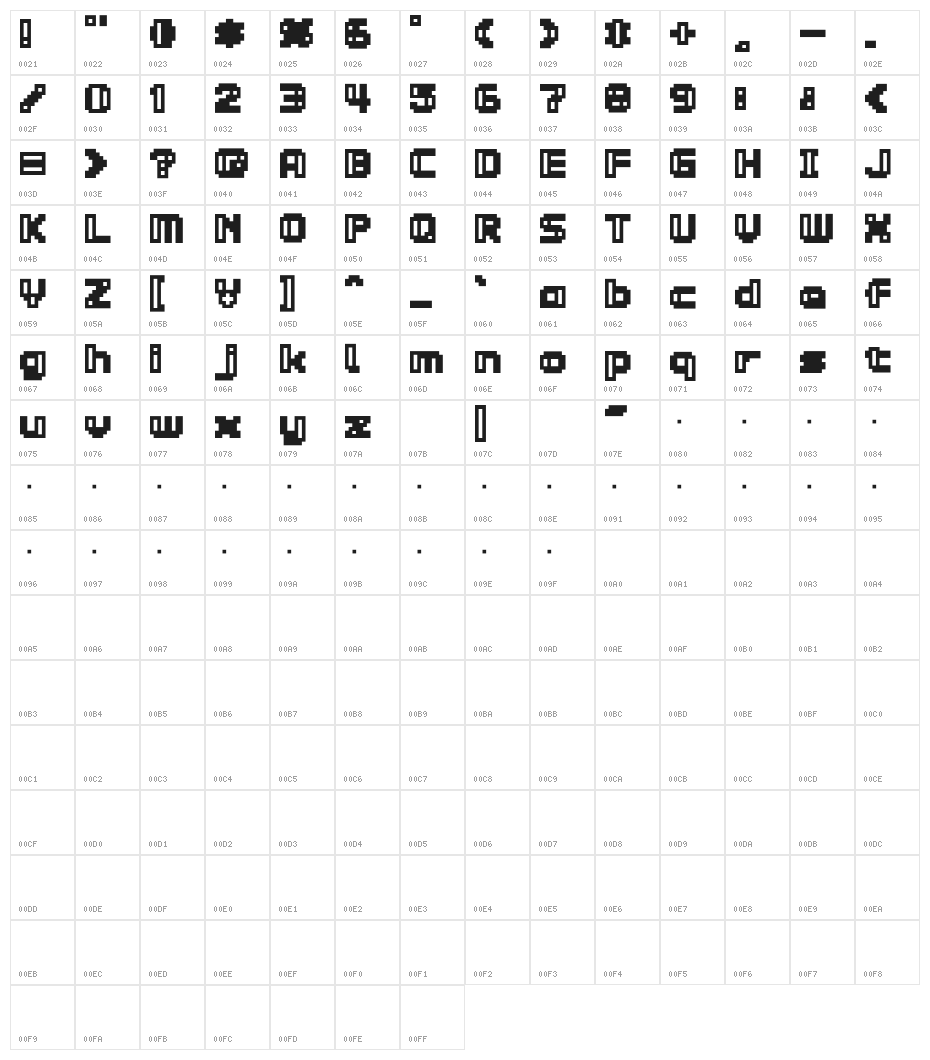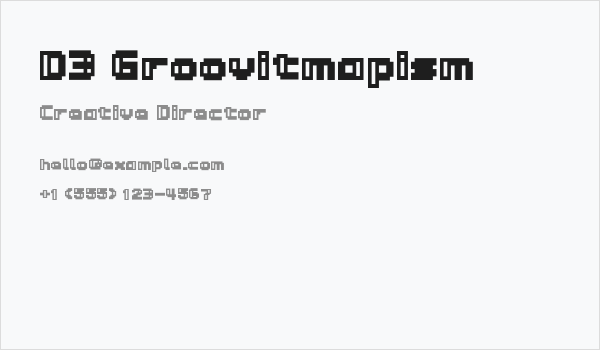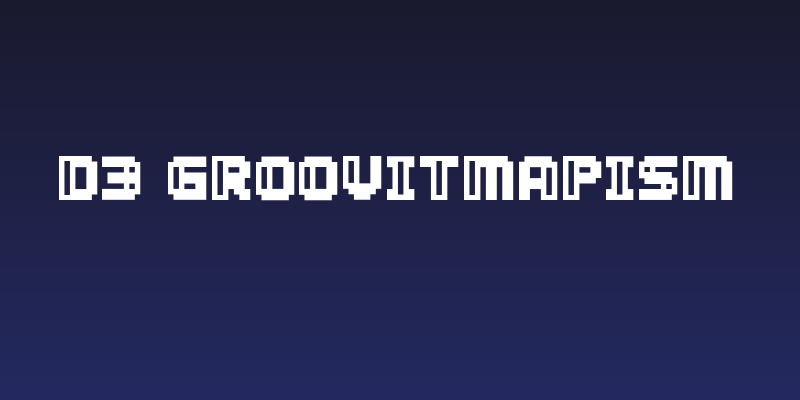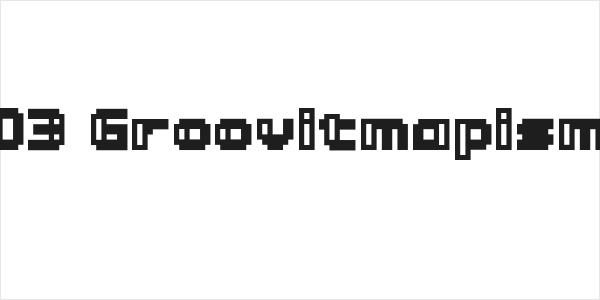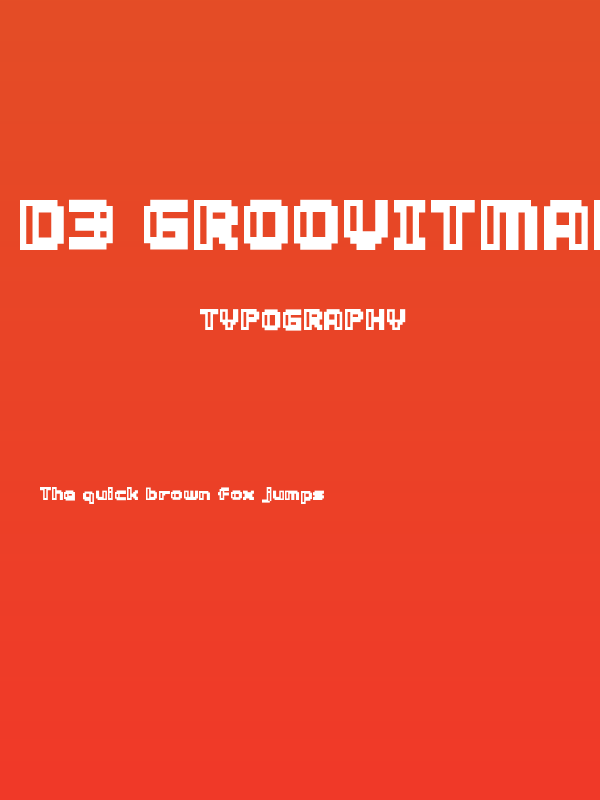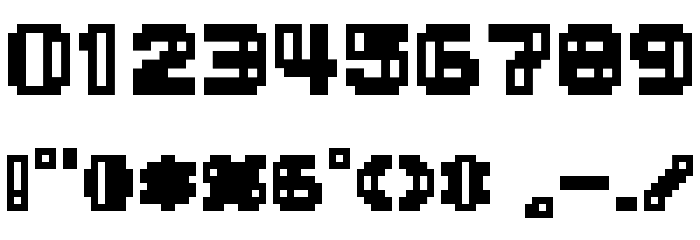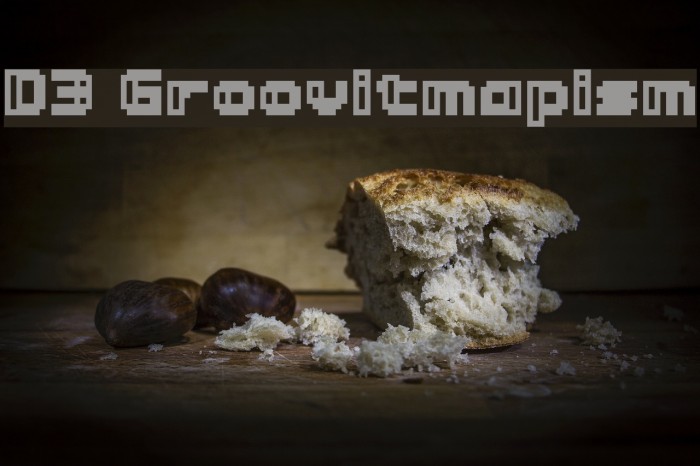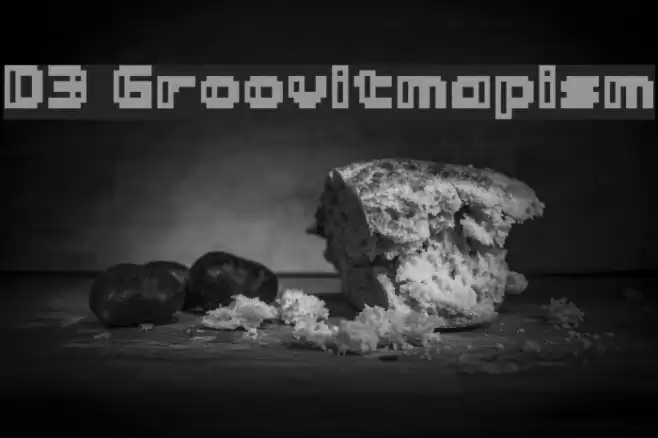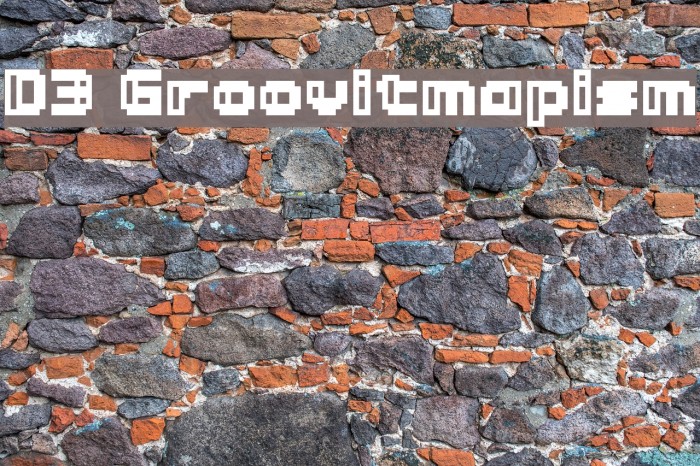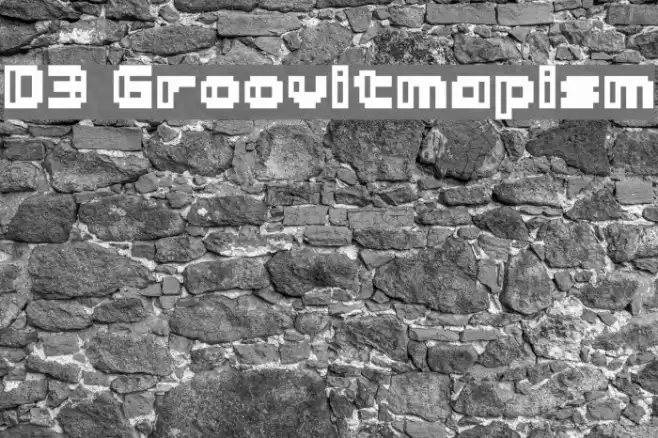
D3 Groovitmapism Font
✎ Pixel
| Gesamtstil | Retro, Digital |
| Anwendungsfall | Headlines, Logos, Digital displays |
| Vorgeschlagene Projekte | Ideal for video game design, digital art projects, retro-themed posters, and tech-related branding. |